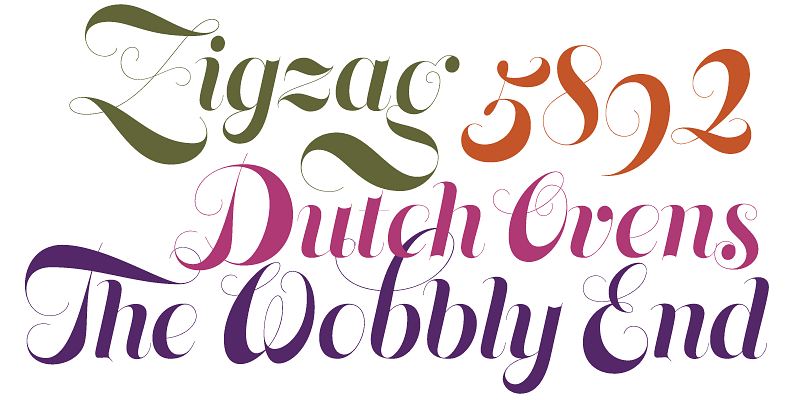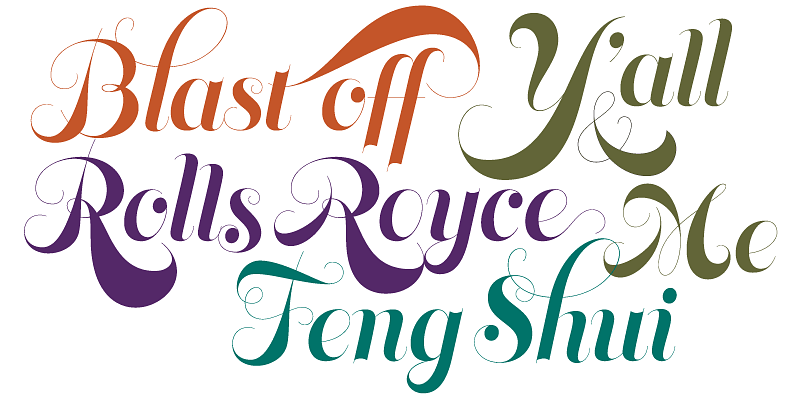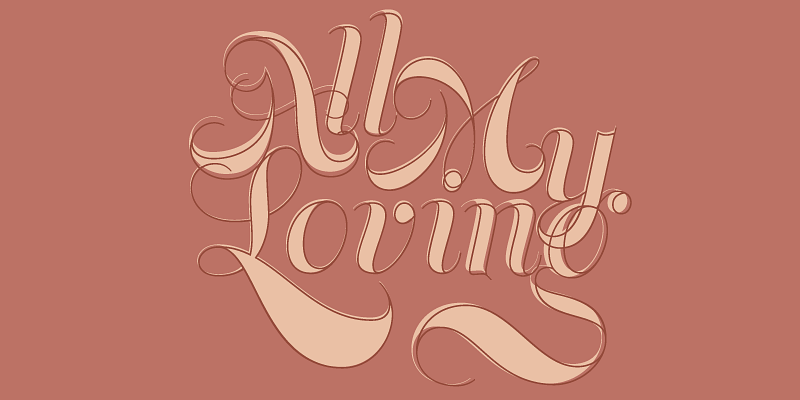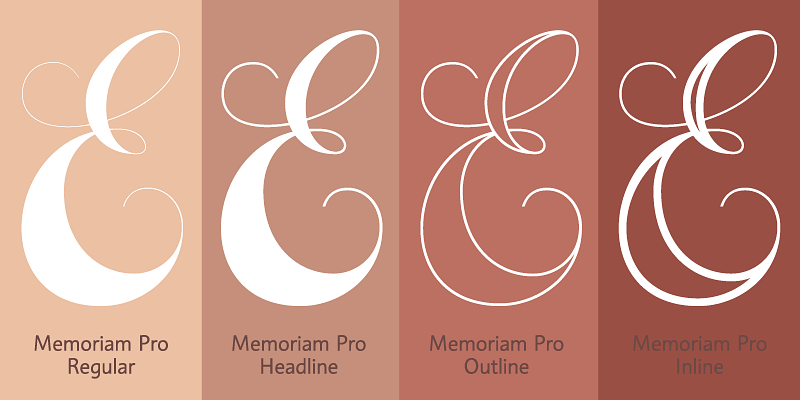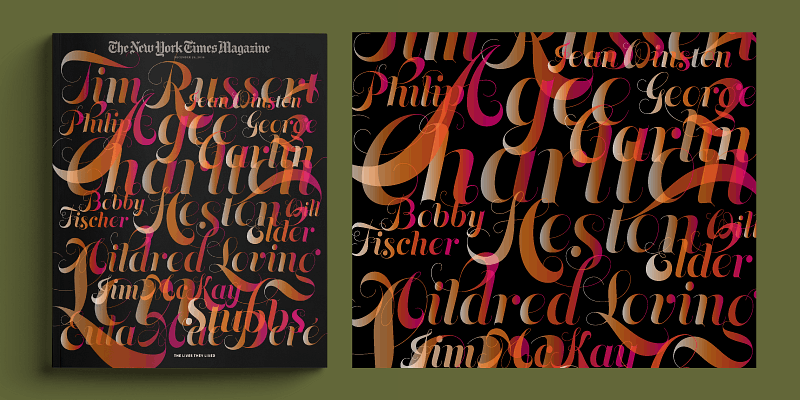
Memoriam fue originalmente encargado por el New York Times para su edición de 2008 “Lives They Lived”, que obtuvo varios premios de diseño. Posteriormente utilizado para uso comercial, se ha convertido en una imagen común en cartelería y embalaje.